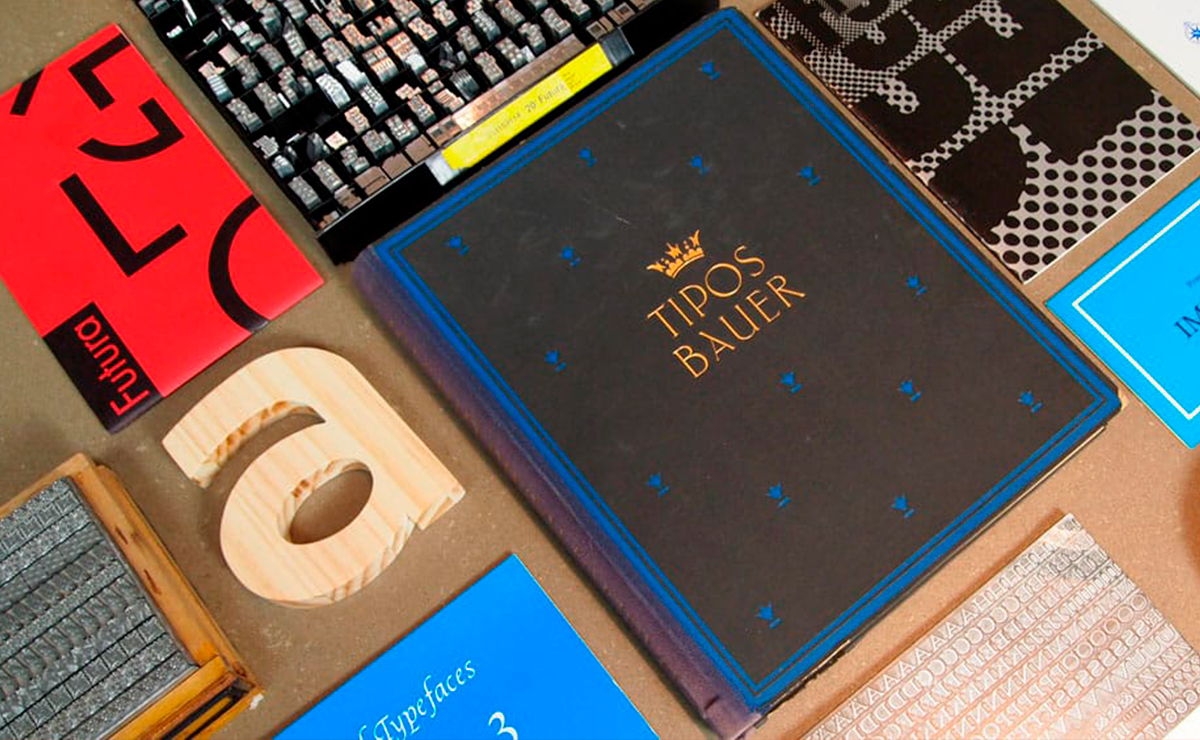
Estamos muy felices de presentaros el curso que hemos preparado con Domestika sobre Tipografía Corporativa.
¡Toda una aventura! No vamos a negar que el rodaje nos pareció bastante duro, los nervios fueron nuestros enemigos y nos costó arrancar. Pero con Miguel, Duprez y Jota (el equipazo de Domestika) todo marchó sobre ruedas… Se nota que tienen callo y paciencia, saben resolver todo tipo de situaciones.
En este curso hablamos sobre tipografía corporativa. Pero además os contamos algo más sobre nosotros comenzando el curso con Wolfgang Hartmann descubriendo la trayectoria de Bauertypes en la era del plomo y contando cómo fueron los orígenes del tipo Futura. Después su sucesora, Vivian Hartmann, explica nuestra transformación en la era digital y los servicios que ofrecemos a día de hoy.
Natalia Weber y Laura Asensio os sumergirán en materia tipográfica enseñando conceptos básicos sobre tipografía, conociendo a fondo cómo es el proceso de diseñar una letra y cómo resolver su visualización en pantalla. Enseñándoos los distintos formatos centrándose en el OpenType y su sinfín de posibilidades. Con el curso, además, podrás descargar un peso de la tipografía Andralis con la cual podrás poner en práctica diferentes prestaciones a través de prácticos ejercicios.
Más tarde os adentrarán en el mercado tipográfico, haciendo un recorrido por las fundiciones más destacadas, conociendo el valor de la tipografía y algo tan importante como son sus tipos de licencias. A través de unos casos prácticos podréis entender mejor la fuerza de la tipografía en la comunicación empresarial, las distintas posibilidades de tipografía corporativa y cómo solucionar problemas a través de la misma.